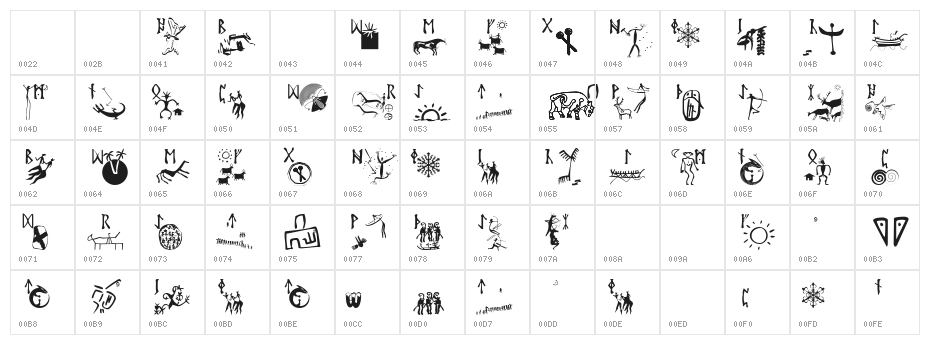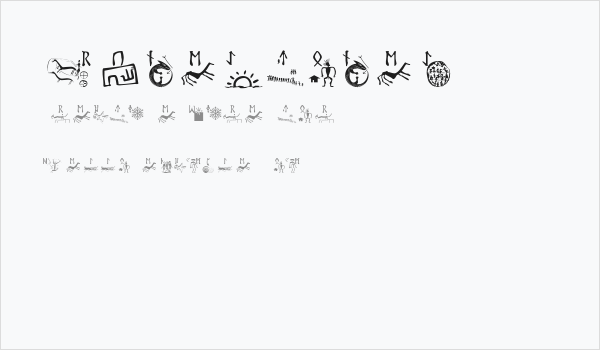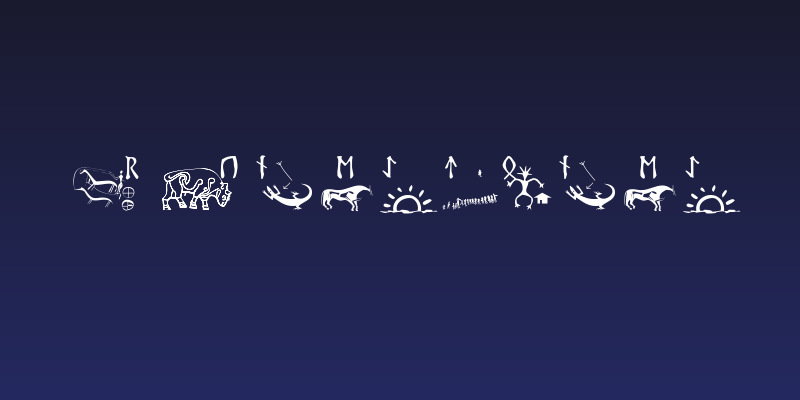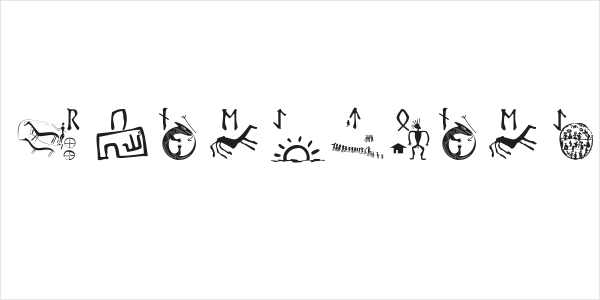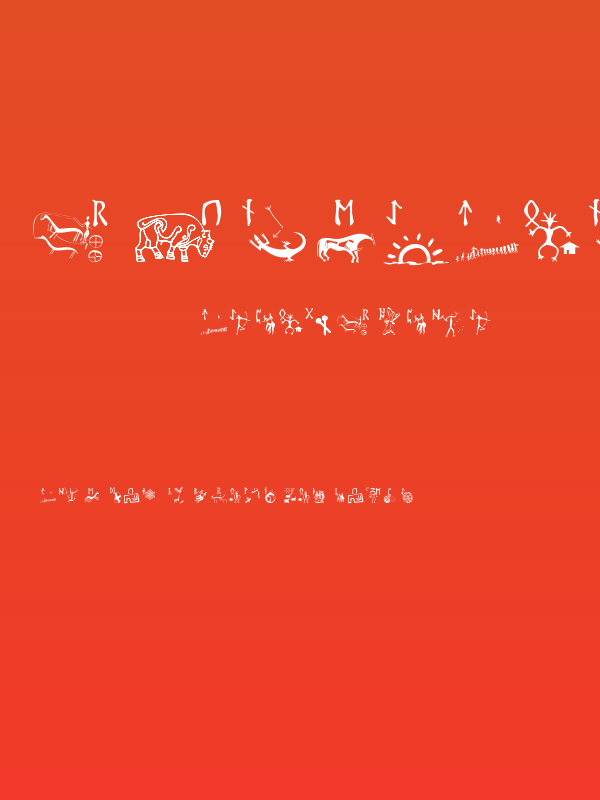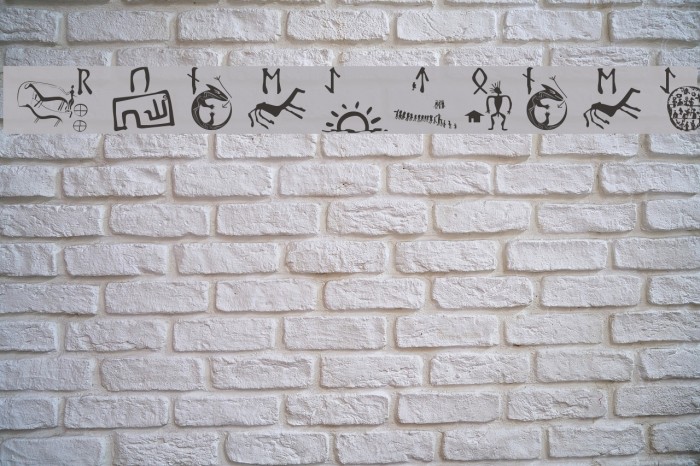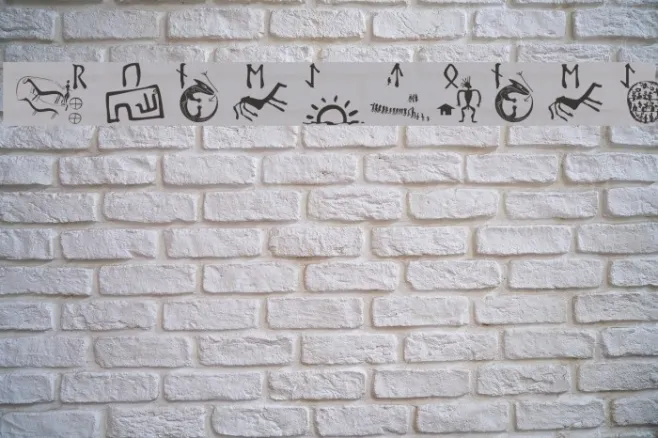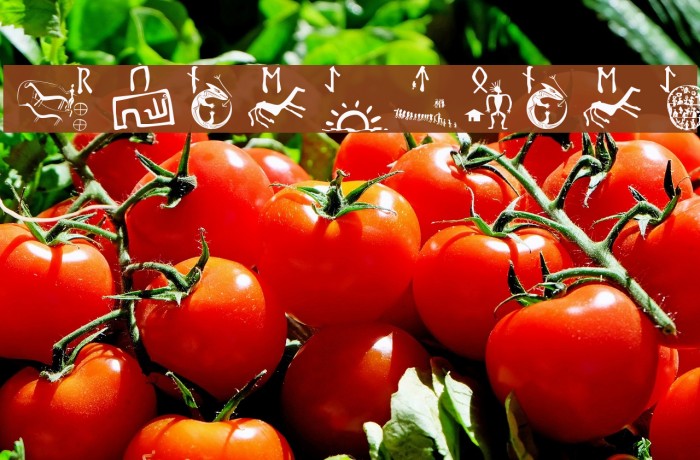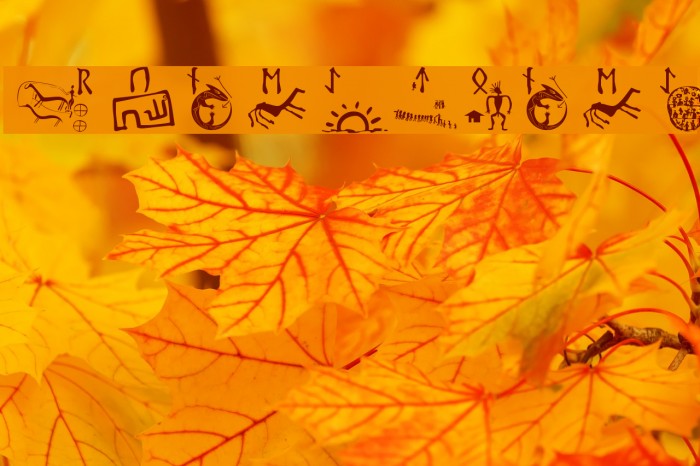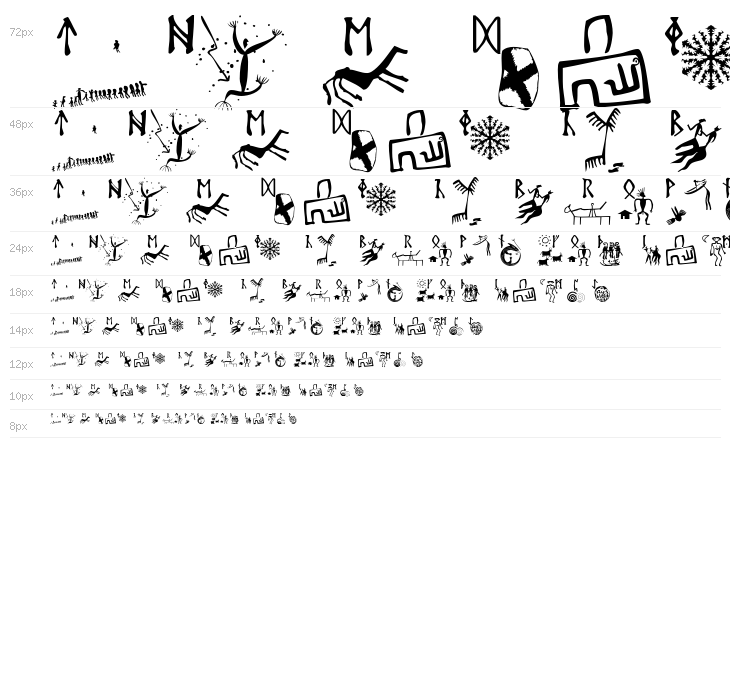
RuneStones Font
| Caso d'uso | Logos, Decorative elements |
| Progetti proposti | Ideal for historical or fantasy-themed projects, such as book covers, game design, or themed event materials. |